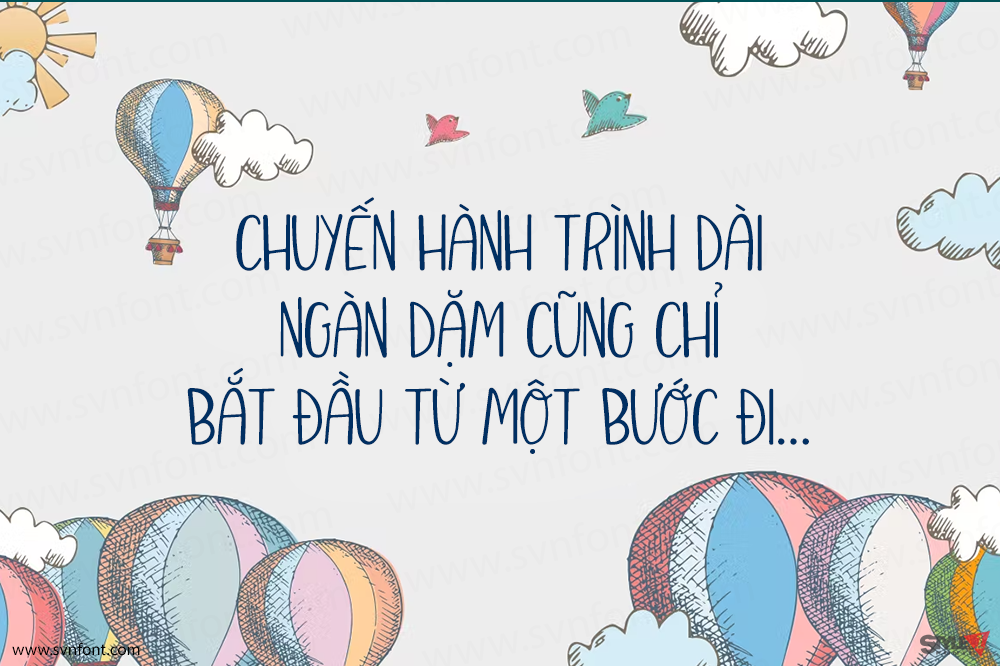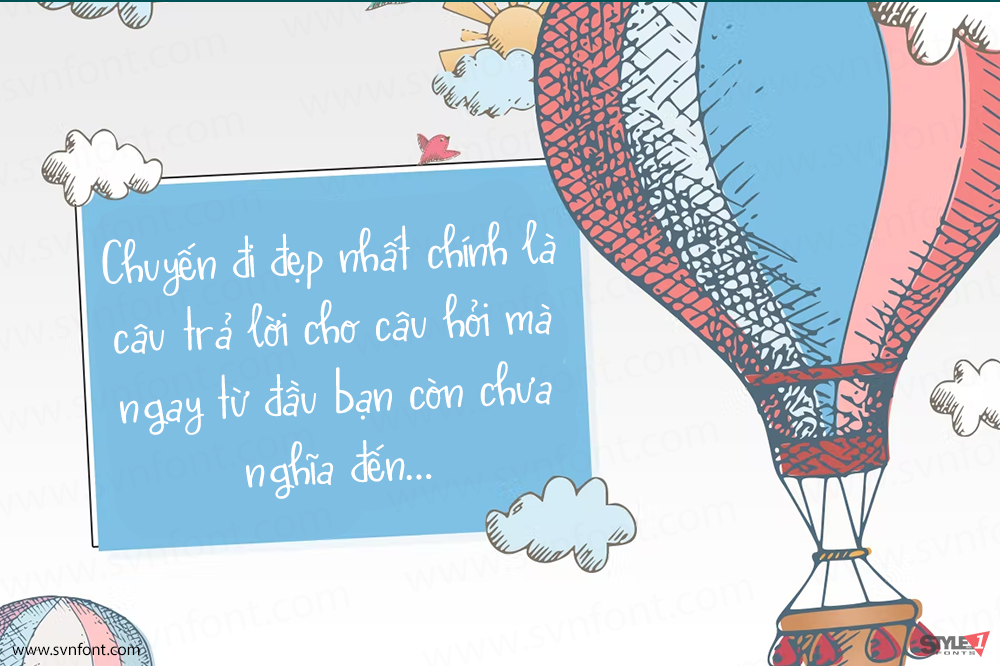
Font chữ này có thể đưa thiết kế của bạn “bay cao, bay xa!” 🚀 Air Balloon dễ thương, vui nhộn và đầy chất mộng mơ. Không chỉ được vẽ tay thủ công, font còn dễ đọc ở mọi kích thước, rất lý tưởng để kết hợp với font khác nhưng cũng đủ cá tính để đứng độc lập. Hãy tự mình cảm nhận nhé!